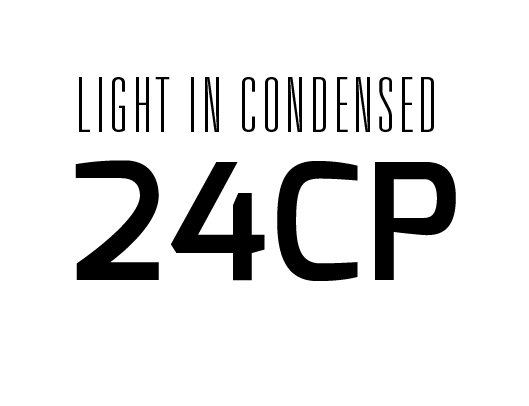
moderne schmal laufende Grotesk mit eigenständigem Charakter gesucht
ich suche nach einer modernen Groteskschrift mit Condensed- und normal laufenden Schnitten und möglichst einer Demi-Bold- und Light-Stärke dabei.
Der Charakter der Schrift sollte etwas eigenständiges mit hohem Wiedererkennungswert haben. Und das nur bei Betrachtung der Versalien und Zahlen CP24.
Alles mit (ausschließlich) Mediävalziffern fällt leider raus.
Ein gutes Beispiel für die Eigenstädigkeit, die ich meine, ist die Exo (auch wenn ich sie wegen der fehlenden condensed-Schnitte mit der Univers mischen musste). Nur der Anstrich der "2" gefällt mir nicht, der sieht eher unelegant aus...
Allerdings brauche ich noch Alternativen... Habt ihr da Ideen?
Die Clan könnte ich mir gut vorstellen …